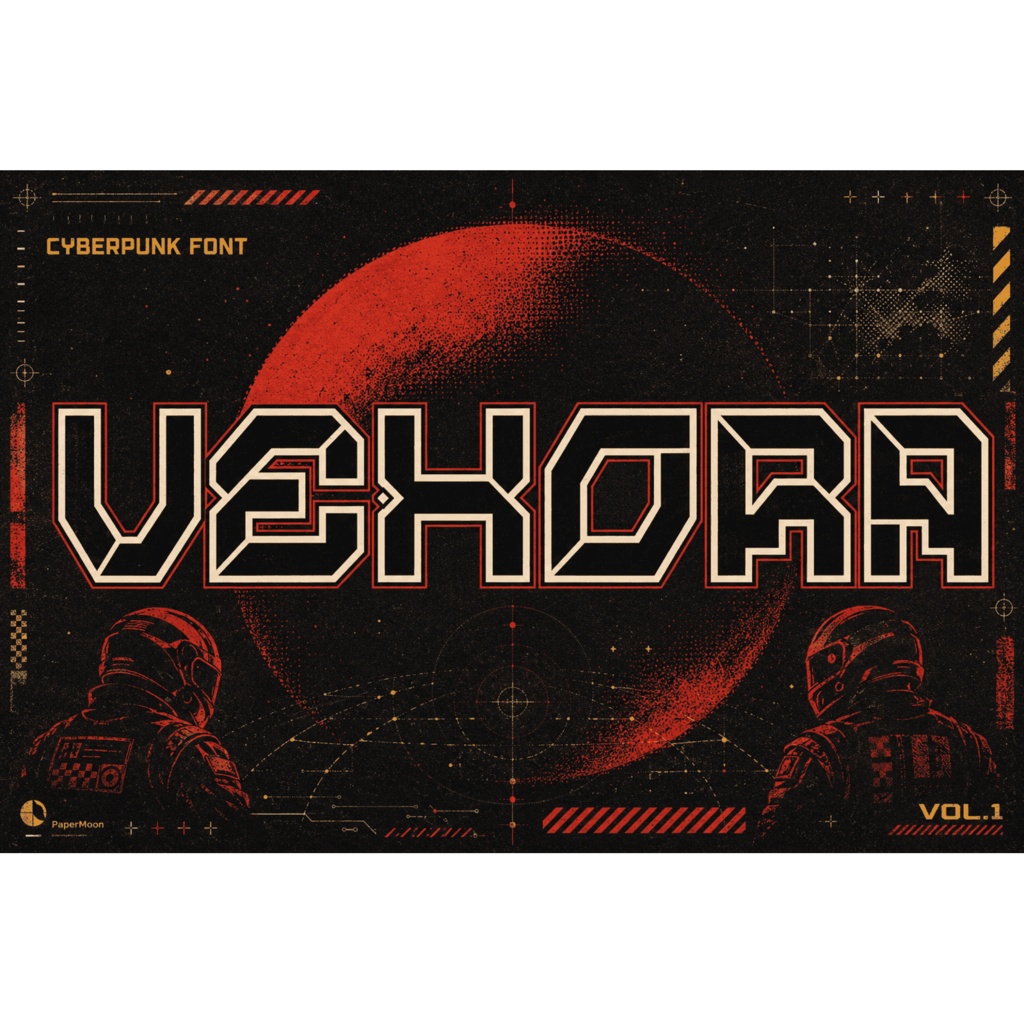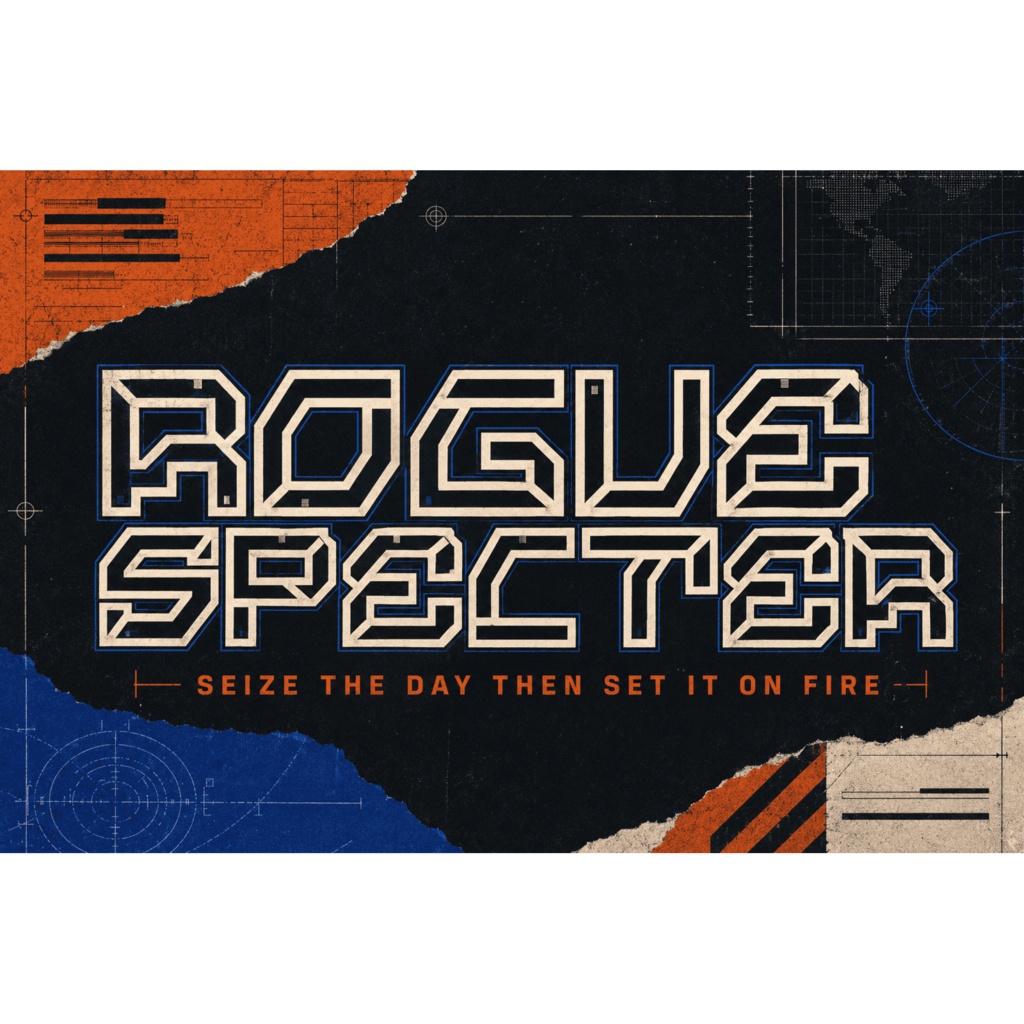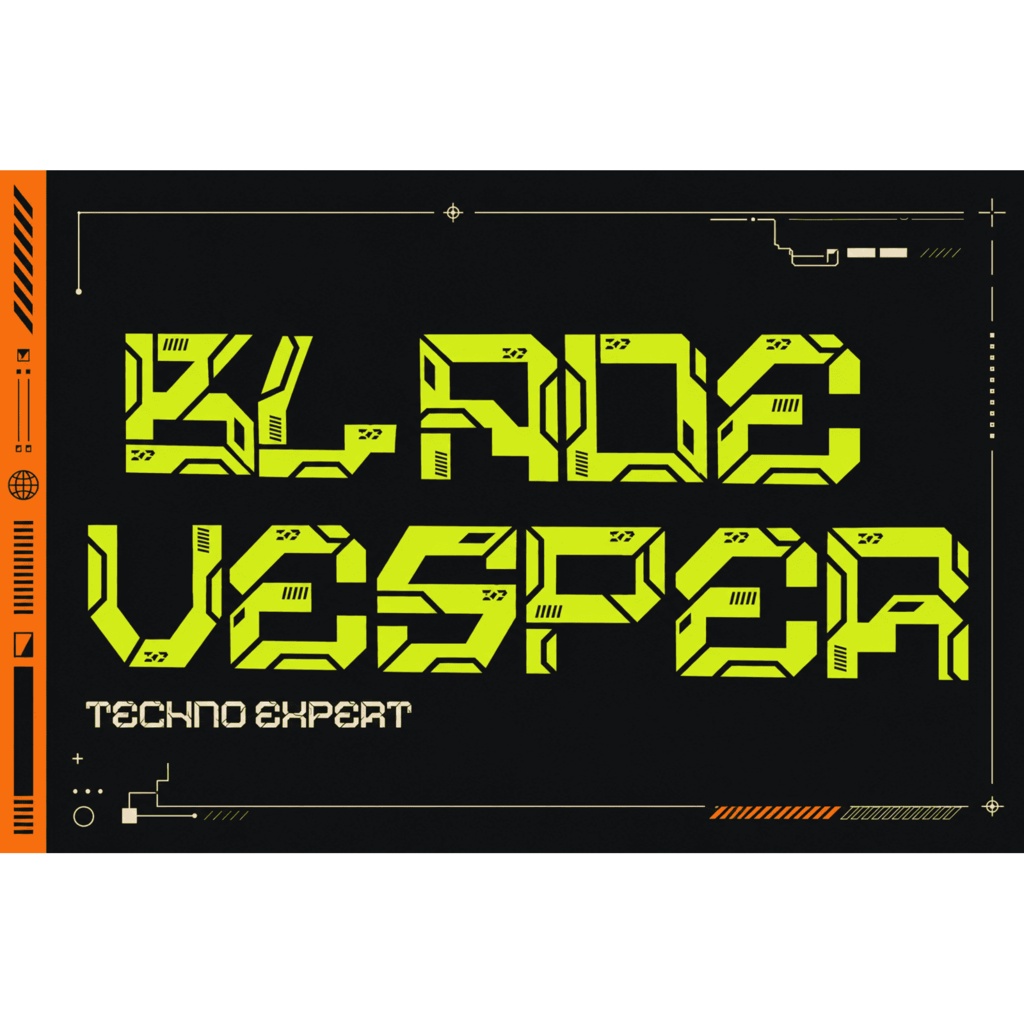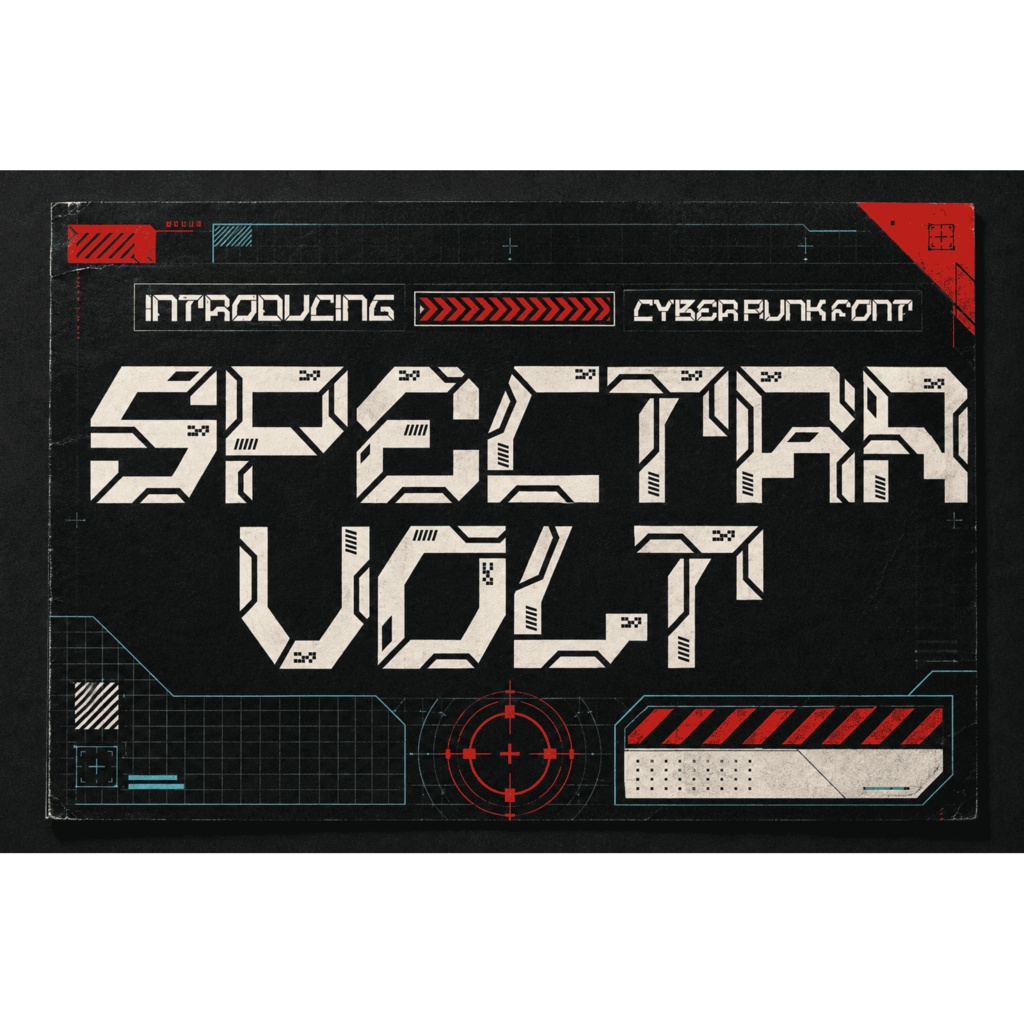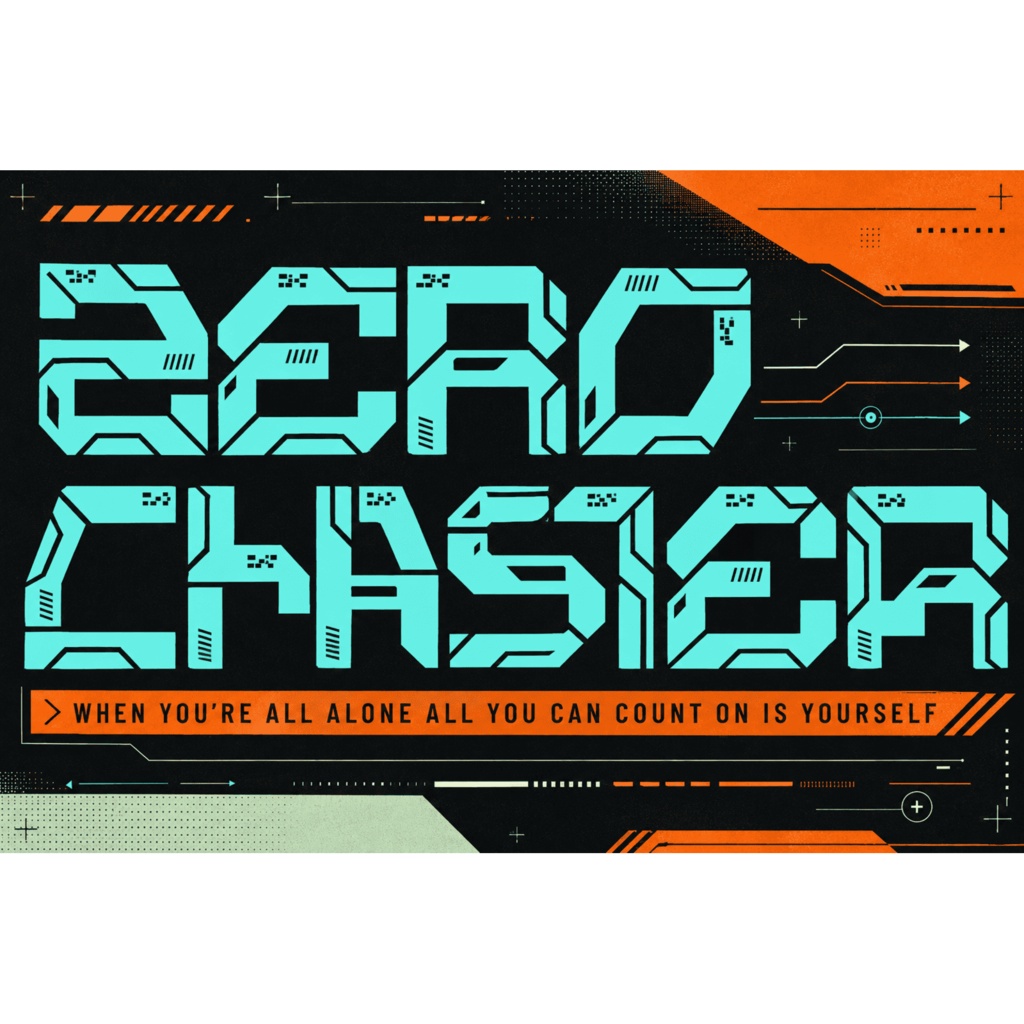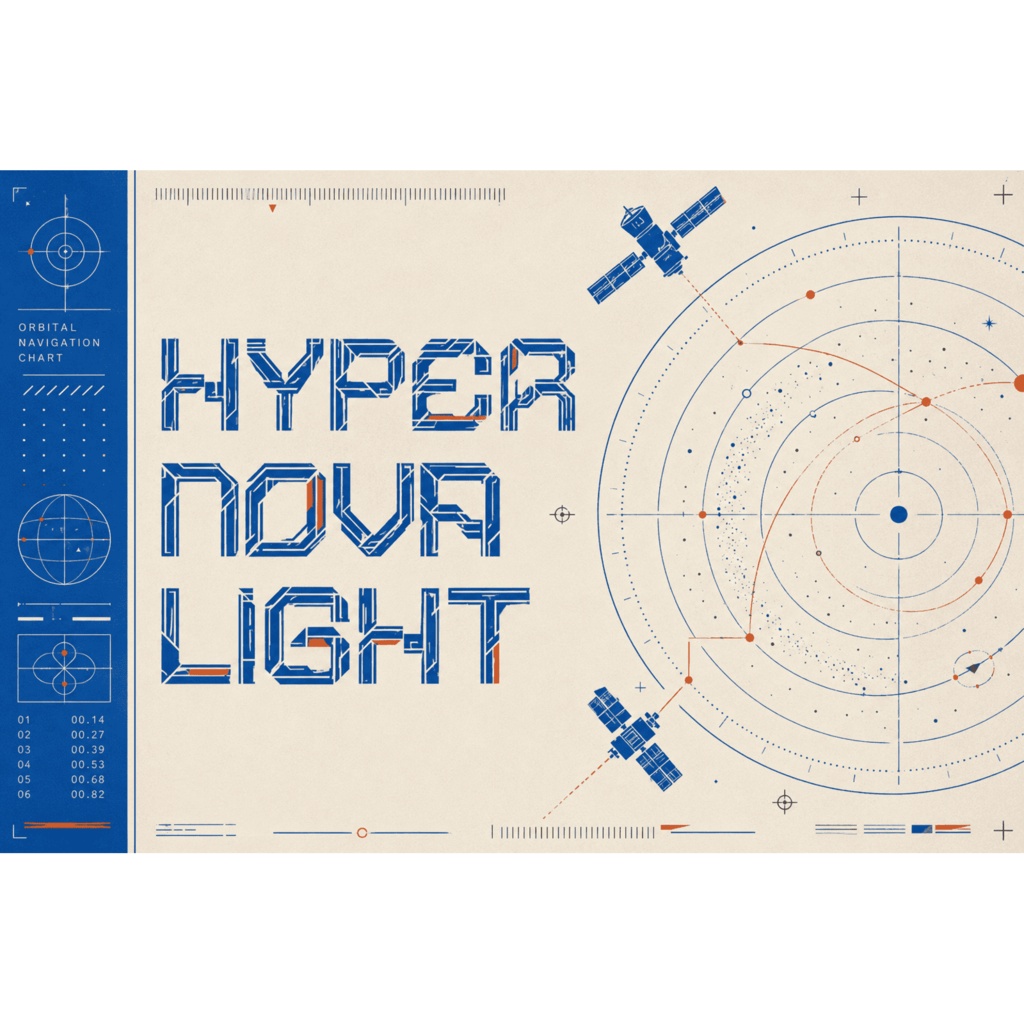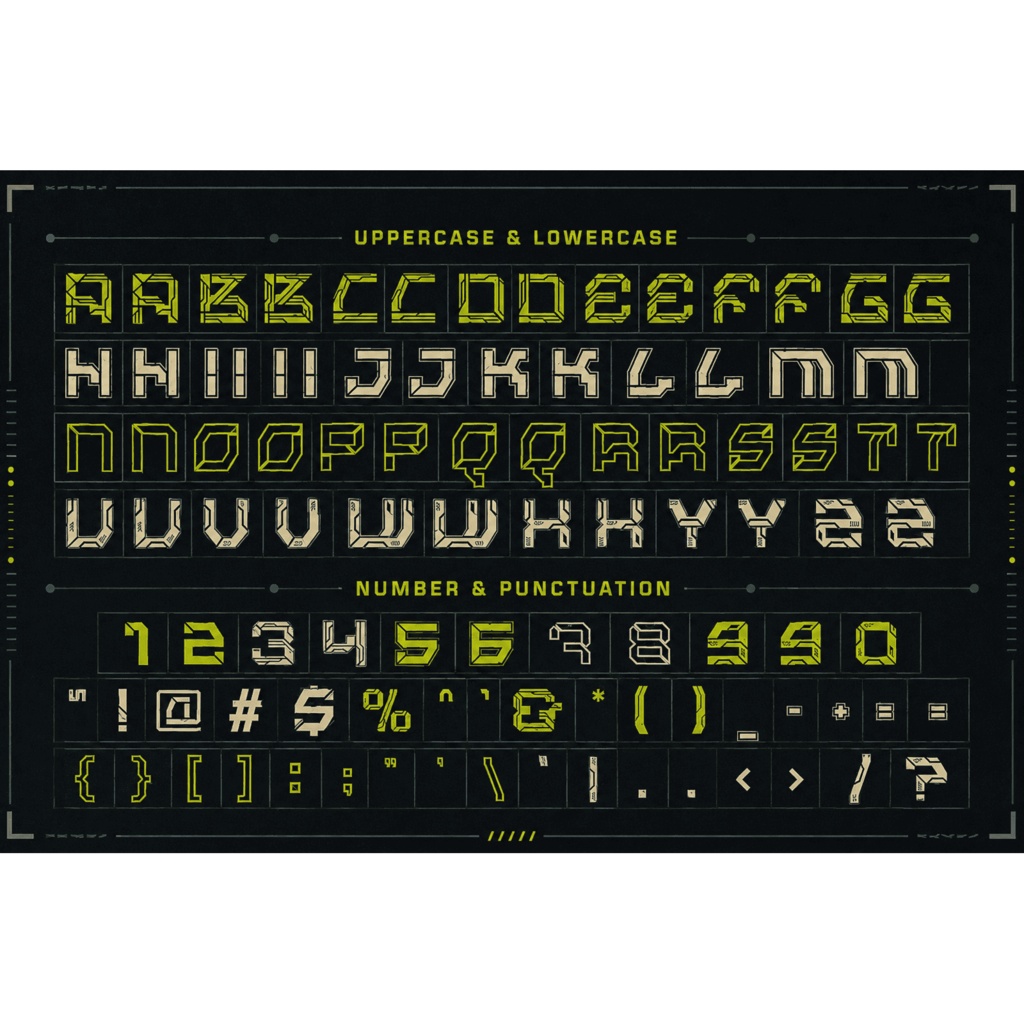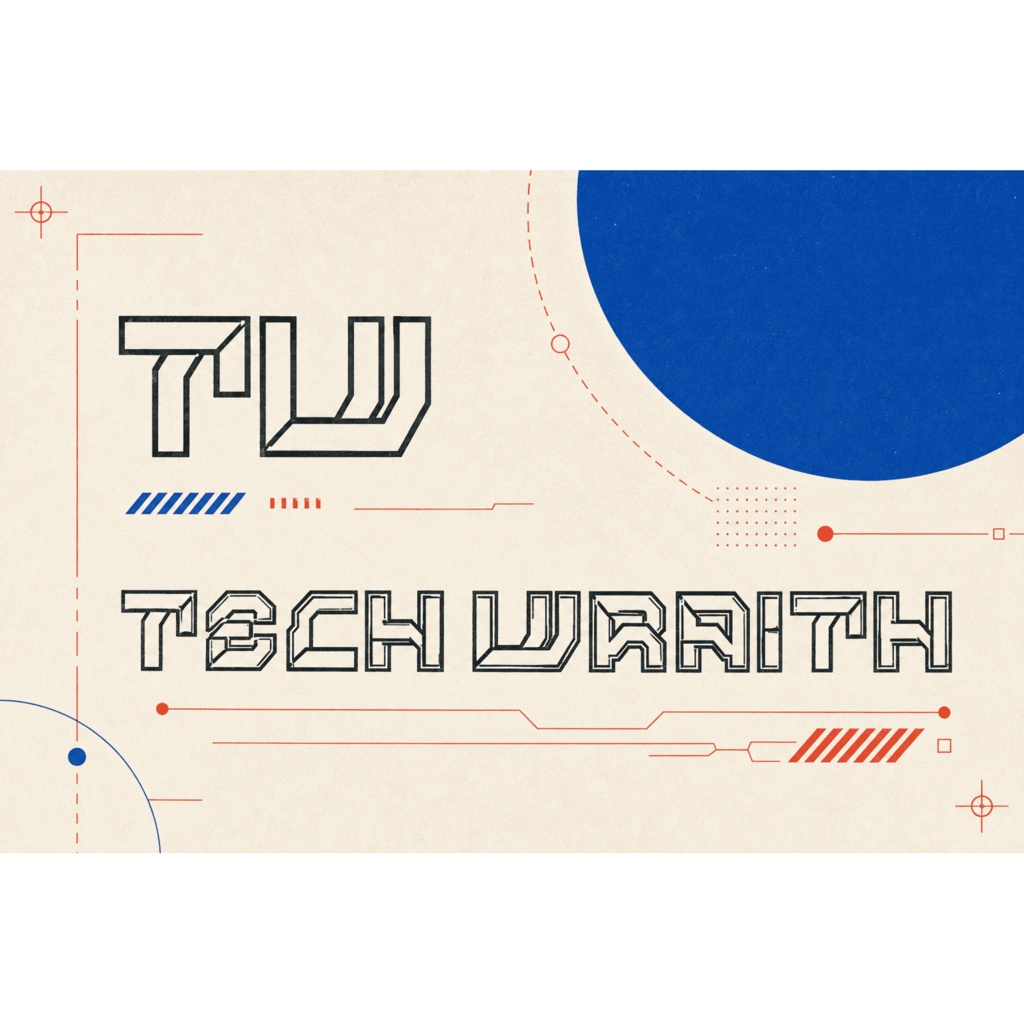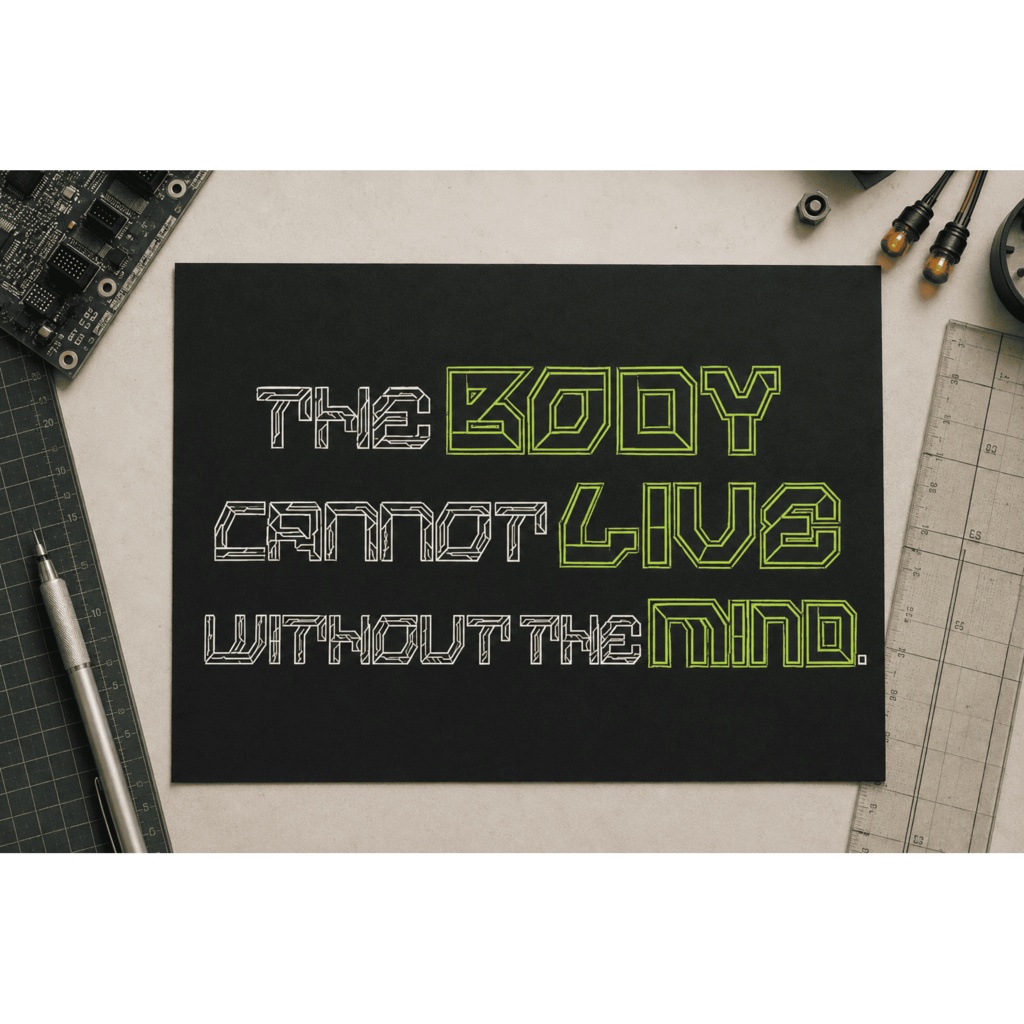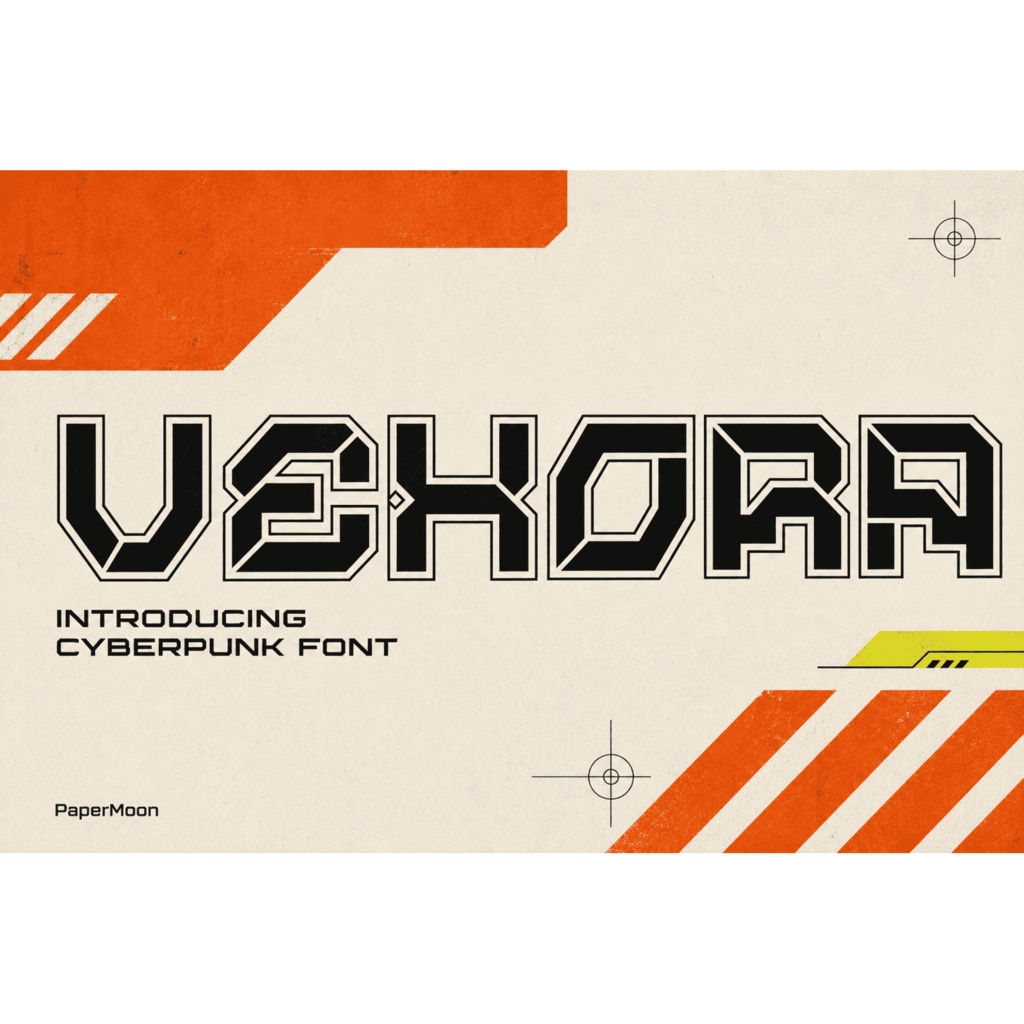
Vexora | サイバーパンク英字フォント / Cyberpunk Display Font
Vexoraは、シャープな角ばったエッジと分割されたデジタル回路風の形状を持つ、サイバーパンク系のディスプレイフォントです。電気的なブルーのネオンや近未来的なビジュアルに合う、ゲームタイトル、ロゴ、テックブランド、ポスター、インターフェース向けの力強いレタリングを作れます。 Vexora is a cyberpunk display font with sharp angular edges and segmented, digital-circuitry-inspired forms. Its electric-blue neon sci-fi direction is suited to game titles, technology branding, logos, posters, packaging, stickers, magazine covers, game interfaces, tech event posters, and cyberpunk merchandise. ### 収録内容 / Included Regular、One、Two、Three、Fourの5スタイルを収録しています。各スタイルはOTF形式とTTF形式で提供されます。 The family includes five styles: Regular, One, Two, Three, and Four. Each style is supplied in OTF and TTF formats. ### 対応文字・機能 / Character Set & Features 大文字、小文字、数字、句読点・記号を収録しています。対応するアプリケーションでは、OpenTypeの異体字や合字を使用できます。フォントはPUAエンコードです。 The font includes uppercase, lowercase, numerals, and punctuation. Supported OpenType alternates and ligatures are available in compatible applications. The font is PUA-encoded. ### 用途 / Uses ゲームタイトル、SFプロジェクト、テックブランディング、ロゴ、ポスター、パッケージ、ステッカー、雑誌表紙、ゲーム画面、テックイベントのポスター、サイバーパンク系グッズなどにおすすめです。 Use Vexora for game titles, sci-fi projects, tech branding, logos, posters, packaging, stickers, magazine covers, game interfaces, technology event posters, and cyberpunk merchandise. ### 形式 / Formats OTF、TTF ### 対応環境 / Compatibility OTFまたはTTFに対応する一般的なデスクトップフォント環境での使用を想定しています。OpenTypeの異体字・合字は、対応機能を備えたアプリケーションで利用してください。 Designed for standard desktop font workflows that support OTF or TTF. OpenType alternates and ligatures require an application that exposes those features. ### 利用許諾 / License ライセンス条件は、この listing 用の supplied facts に含まれていません。商用利用、クライアント制作、商品化、埋め込み、再配布などの可否は未確定です。購入前に、最終的にBOOTHへ設定するライセンス本文を確認してください。 The applicable license terms were not supplied for this listing. Commercial use, client work, merchandise, embedding, redistribution, and other permissions are not stated here. Confirm the final BOOTH license text before purchase or commercial use. ### 注意 / Note プロモーション画像に表示されるモックアップ、装飾エレメント、シャドウ、ストックグラフィックはフォント本体に含まれません。 Preview mockups, decorative elements, shadows, and stock graphics shown in promotional imagery are not included with the font.